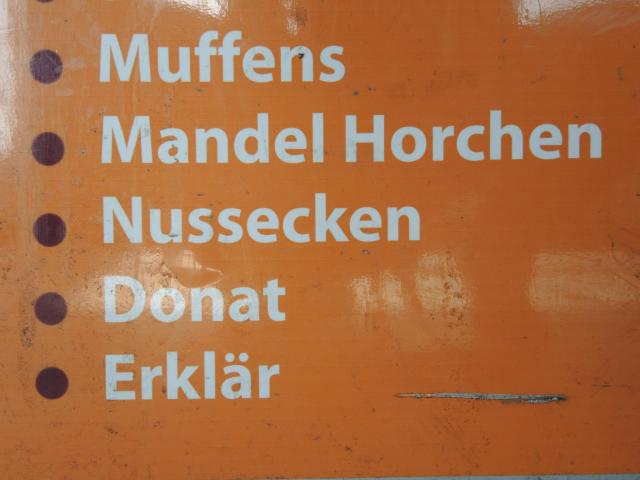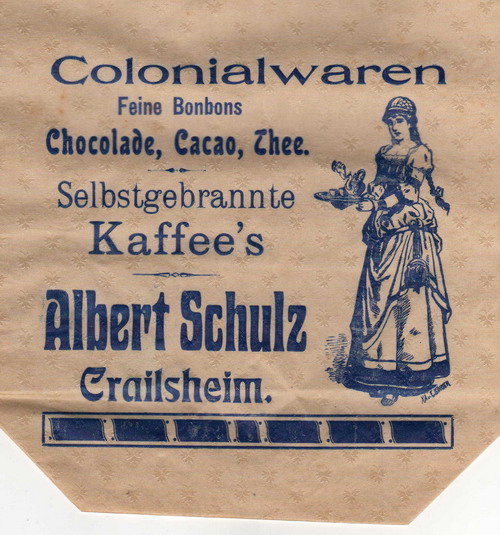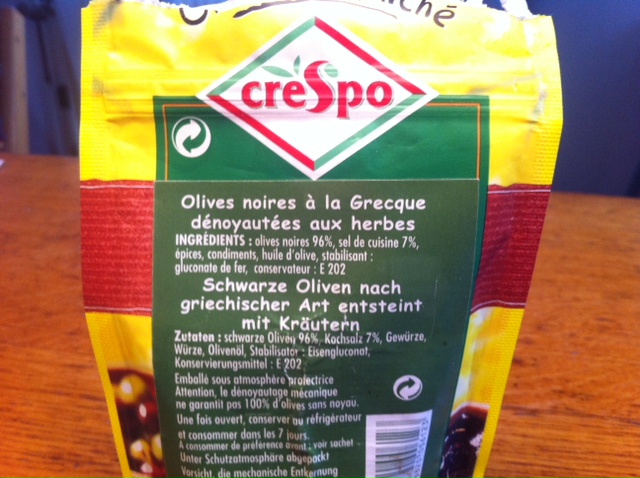
Dieses tolle, Erklär-ungsbedüftige Werk, bei dem man den Mandeln wohl gehorchen muss findet sich auch auf Bastian Sicks Seite unter den Fundstücken.
Schön auch:
Hierzu hatte auch ich mal ein Erlebnis: ein Supermarkt in Hamburg hatte an den Hauswänden, welche den Parkplatz umrahmten handgeschriebene Plakate mit den Sonderangeboten. Offensichtlich war ein Auszubildender damit beschäftigt, auf die mit frischem, weißen Papier beklebten Plakatwände die aktuellen Sonderangebote zu schreiben - ja, noch von Hand. Und so schrieb der gute mit breitem Pinsel: "Jachtwurst 100g DM 0,99" (oder so) - ja, so spricht man diese Wurst da auch aus. Ich schaute zu dem eifrigen Maler hoch, überlegte kurz, und wies den armen Jungen auf den Fehler hin: "Das schreibt sich dann aber mit Y!"
Der Ärmste schaute etwas verwirrt, meine dann aber, er wolle doch lieber seinen Chef fragen...
Als ich nach dem Einkauf zur Plakatwand schaute, stand da dann tatsächlich für die nächste Woche: Yachtwurst - nun ja, auf der See schmeckt die Wurst bestimmt genau so gut, wie im Wald.
Interessant und auch eigenwillig! Befremdlich erscheint mir der freihändig gesetzte Text in serifenloser Schrift unten, der die Produkte aufzählt. Auf mich wirkt er wie ein Fremdkörper in der Komposition.
Ich habe das auch gar nicht gewertet. Natürlich, es ist ein chaotisches Schriftmusterblatt wie auch boernies obiges Beispiel. Aber es ist, zumindest was die einzelnen Schriften angeht, bemerkens-wert. Die Fundstücke, die hier Erwähnung finden, sind ja durchaus nicht alle typographisch ideal.
die "griechische Art" ist wohl, grüne Oliven zu verwenden und diese mittels Eisengluconat (siehe Zutatenliste) schwarz zu färben. Eine leider zulässige totale Frechheit.
… nach griechischer Art entsteint … ahso.
Ist doch klar: der großkapitalistische Entsteiner zahlt keine Steuern, sondern kassiert EU-Beihilfe für jeden Stein! ;-)
Das passt hier irgendwie rein: http://www.a2591.com/2010/12/minimalist-effect-in-maximalist-market.html
Ich empfinde, insbesondere nach meinem Tschichold-Flashback heute morgen, die Reduzierung als Gewinn, zumal die Schriften dann irgendwie majestätischer rüberkommen. Und es ist eine schöne Bestätigung der These, dass gutes Design dann gut ist, wenn nichts mehr wegzunehmen ist (ich kann mich leider grad nicht erinnern, wer das sagte: Weidemann? Der Mensch, der für Braun designte? Irgendeine Größe der Weltliteratur (ich würd es ja gerne einem Griechen zuschreiben, doch da bin ich mir äußerst sicher, dass das ihrem Verständnis der Realität widerspricht).
»Vollkommenheit entsteht offensichtlich nicht dann, wenn man nichts mehr hinzuzufügen hat,
sondern wenn man nichts mehr wegnehmen kann.«
Antoine de Saint-Exupéry, Terre des Hommes (Wind, Sand und Sterne)
Jony Ive designs Xing (das ist zwar nicht wirklich von Sir Jonathan, aber kein Fake):